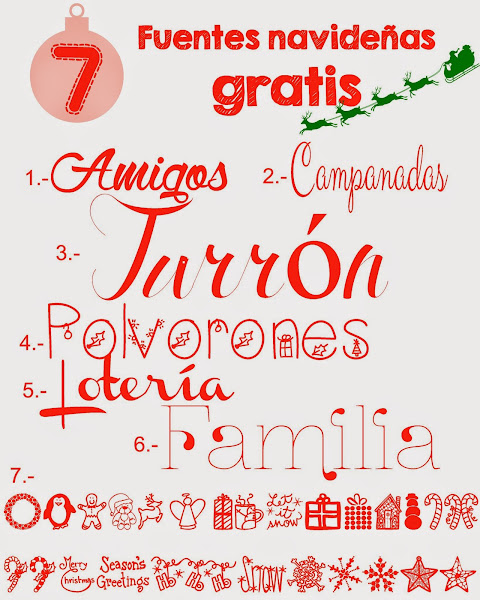
Confesiones y 7 Tipografías Navideñas Gratis!
Tengo que confesarlo.Hace tiempo que tengo un problema:
Estoy enganchada a las tipografías.
Ya me lo avisaron pero no hice caso...
Y es que el mundo de las tipografías tiene límites de infinito elevado a infinito.
Y después llegan los "Dingbats" que son fuentes que no son fuentes! Son dibujitos!!!! walaaaaa!
Descubres que la Comic Sans es una cagada y empiezas haciendo cartelitos y jugueteando con cuatro o cinco letras molonas y acabas descargandote más de 200. Y nunca son suficientes!
¿que no son suficientes 200 tipos de letra?
Pues no, por que siempre descubres uno nuevo más bonito que el anterior.
Y lo peor no es eso... Lo peor es que voy por la calle, veo un poster o un anuncio en la parada de autobús y no puedo evitar analizarlo y preguntarme qué fuente será esa tan chula...
Te das cuenta de que tienes un problema cuando en lugar de preguntarte qué fuente es resulta que la identificas!
-"Anda mira! La Topeka combinada con la Sketch Block queda chula..."
Pero claro esto lo pienso, no lo digo en alto ni se lo digo a mi marido... Así que me está comiendo por dentro!
Necesito crear monstruos zampa-letras como yo para poder compartir inquitudes tipográficas.
Así que para empezar os he hecho un recopilatorio de letras navideñas.
Para que hagais vuestras láminas navideñas, tarjetas para los regalos, christmas...
Con un poco de suerte alguna de las 20 personas que leeran esto se enganchará a las tipografías.
Aqui lo teneís:
1.-Wolf In The City
2.- Clicker Script
3.- Antrokas
4.- Christmas Eve
5.- Channel
6.-Znikomit nº24
7.- Christmas Doodles by Austie Bost
Cómo estar tarjetas que hice yo la semana pasada para poner el nombre en los regalitos de los reyes y así diferenciarlos. Eso si, esta vez a mano: